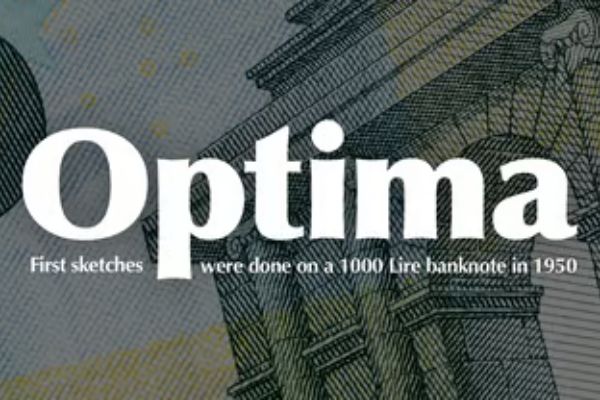
Optima® Pro Demi Bold Italic
Optima 秉承了罗马风格的特征,在具备独特吸引力的同时还保持了易读性和多功能性。Optima用于传达经典理念和当前趋势,雅诗兰黛将其用作官方字体,英国零售商 M&S 将其用在公司logo,Traveller 科幻角色扮演游戏中也使用了它。Optima 还被用在华盛顿越南退伍军人纪念碑和美国总统竞选活动中。它几乎可以与任何衬线设计和大量无衬线字体完美融合,支持大多数中欧和许多东欧语言的扩展字符集。